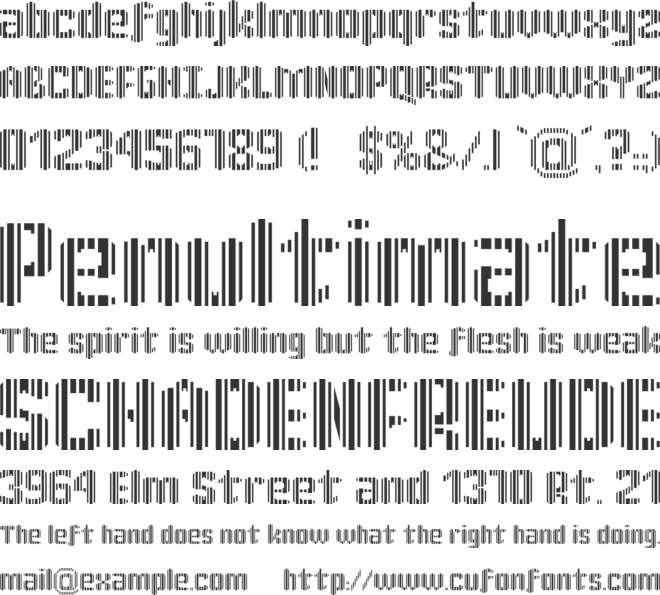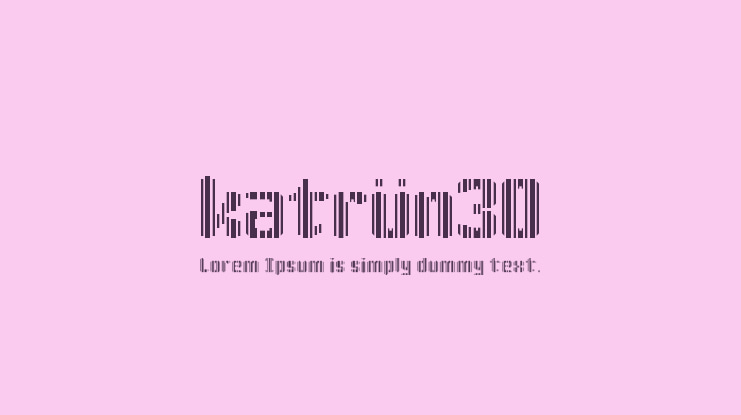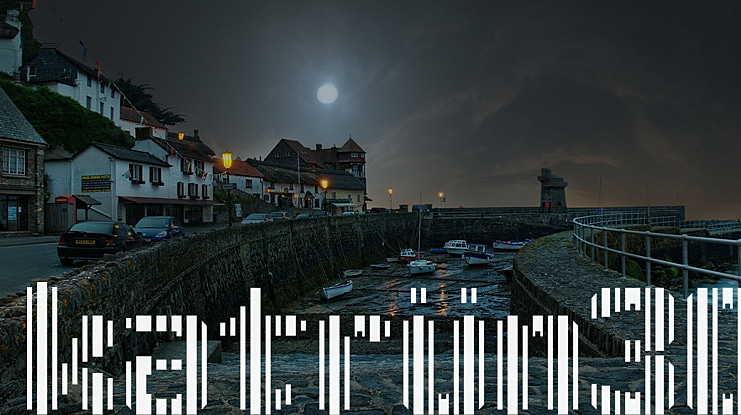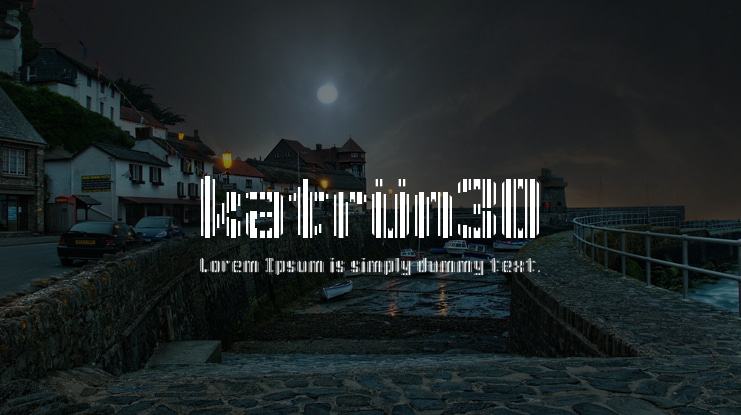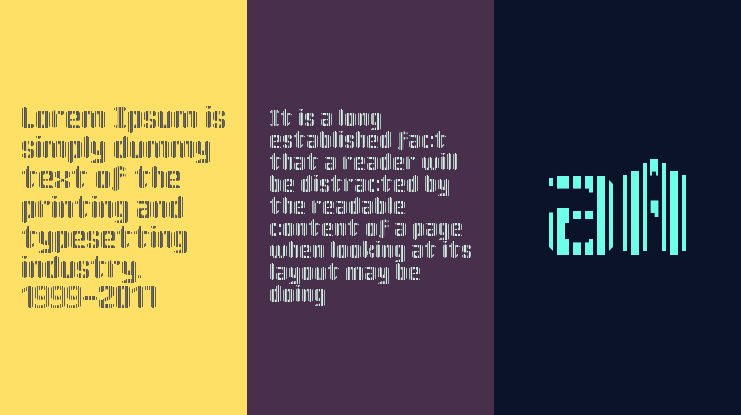
katrün30 Font
Ignacio "Kzuz" Ponce
La simplificación de las formas de los telares mapuches como referente único y directo este caso de estudio para poder generar una tipografía que muestre o deje ver rasgos de sus formas, la composición y forma de armado de estos. Katrün del mapudungun cortar/cortarse y 30 debido a la regla utilizada para la creación de esta tipografía, se realizan cortes en cada carácter cada treinta em square (medida utilizada en Fontlab Studio 5) y los anchos ortogonales de cada una varían entre dicho numero o su doble, es decir, sesenta em square, dicha regla es utilizada también para la altura de equis, ascendentes, descendentes, mayúsculas, signos de puntuación, números, etc.